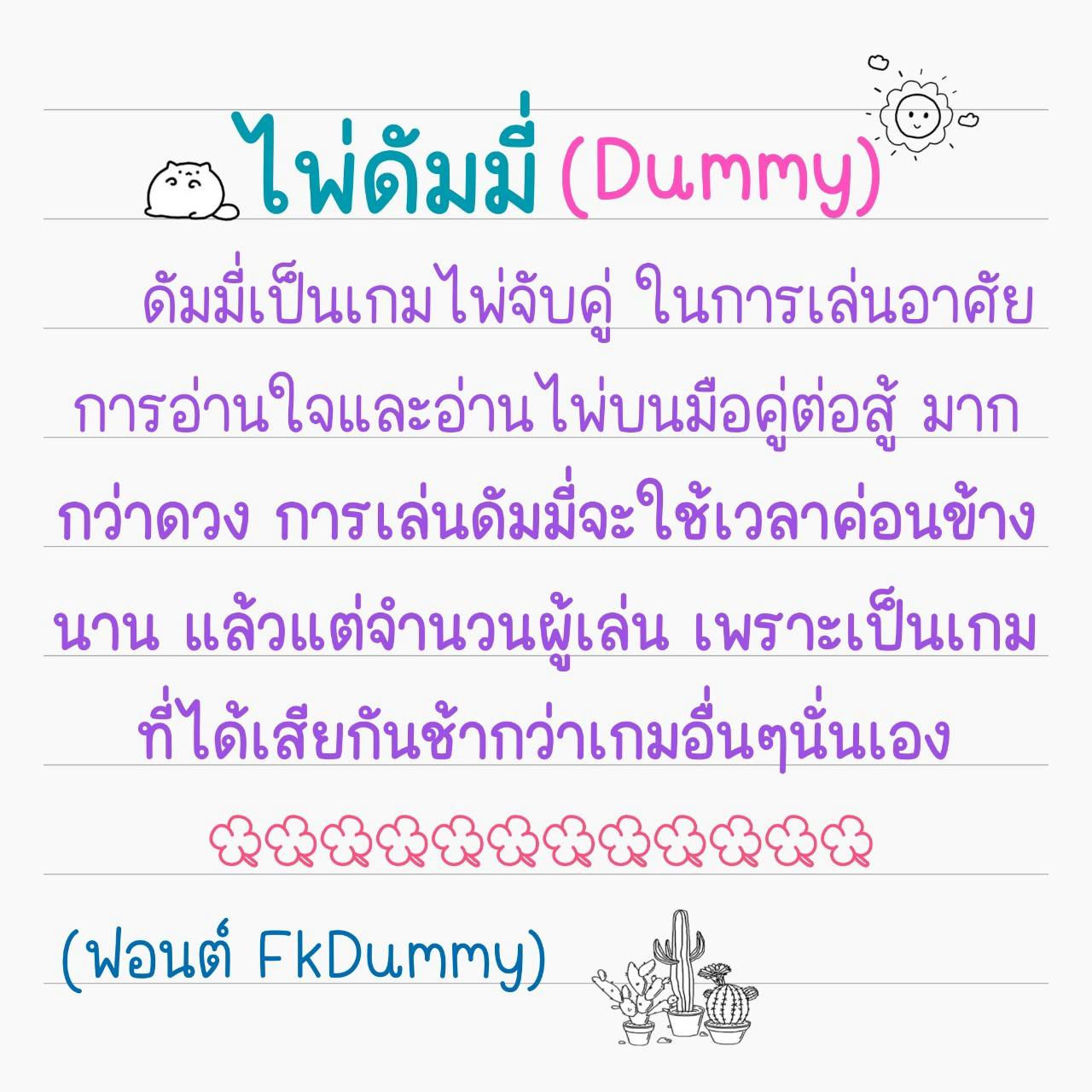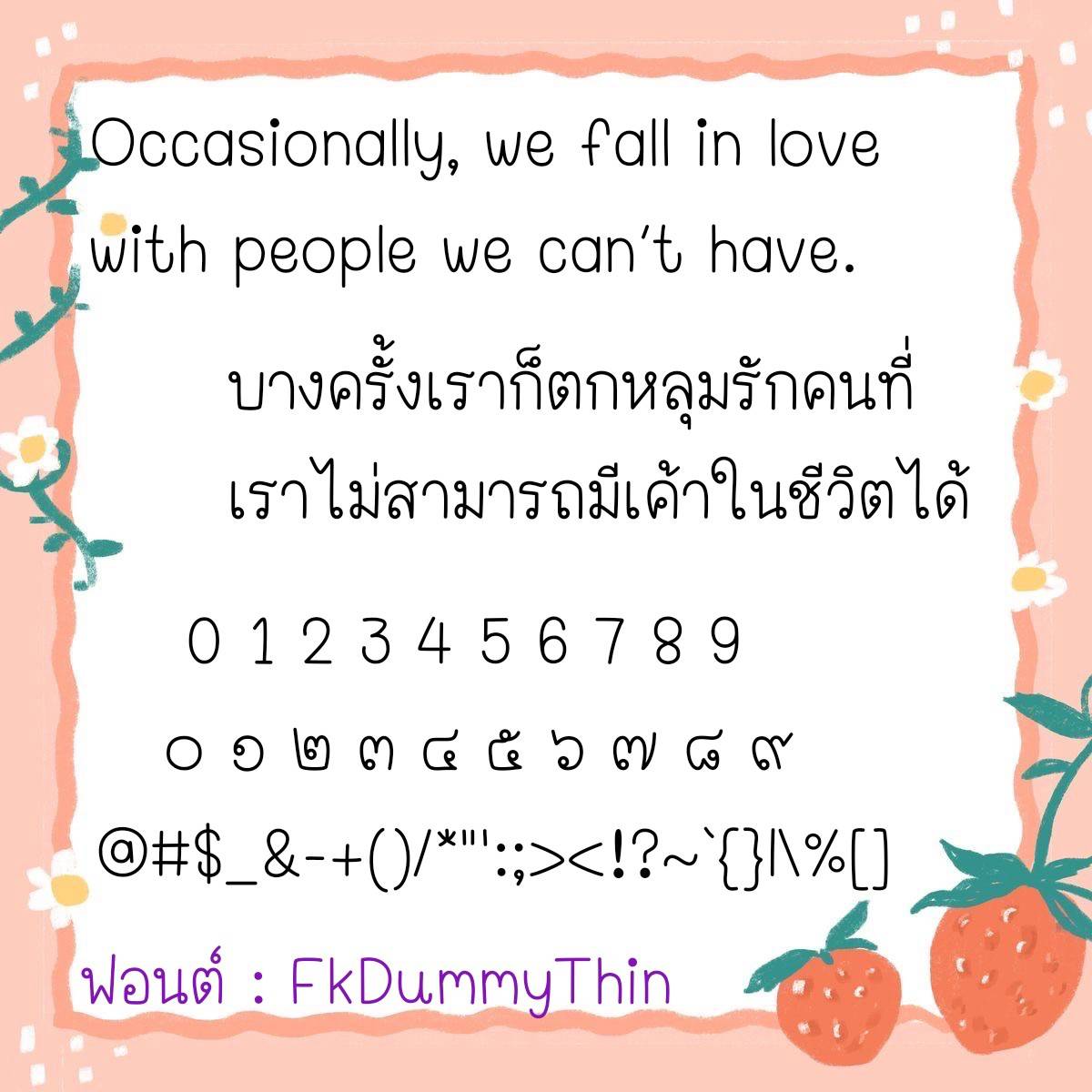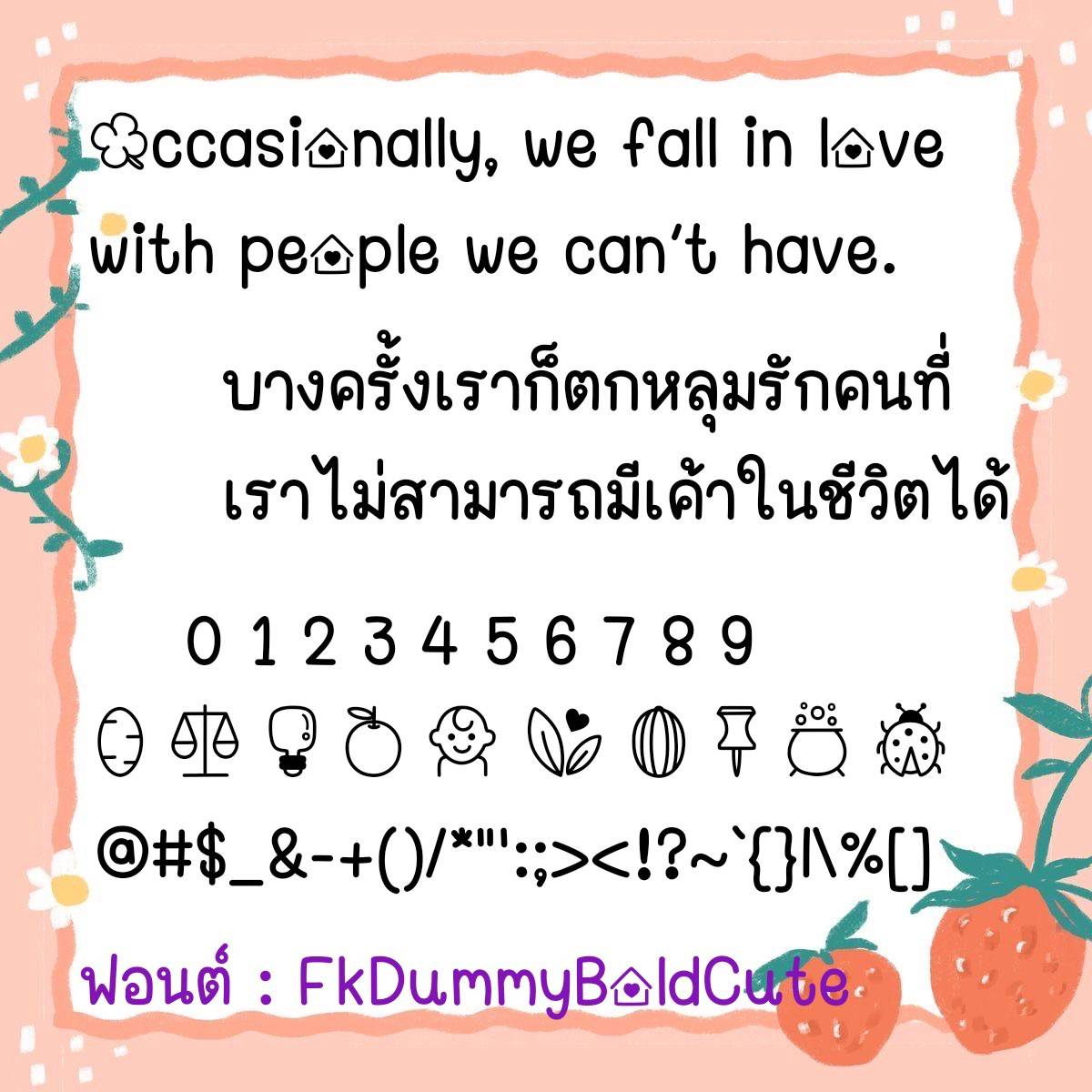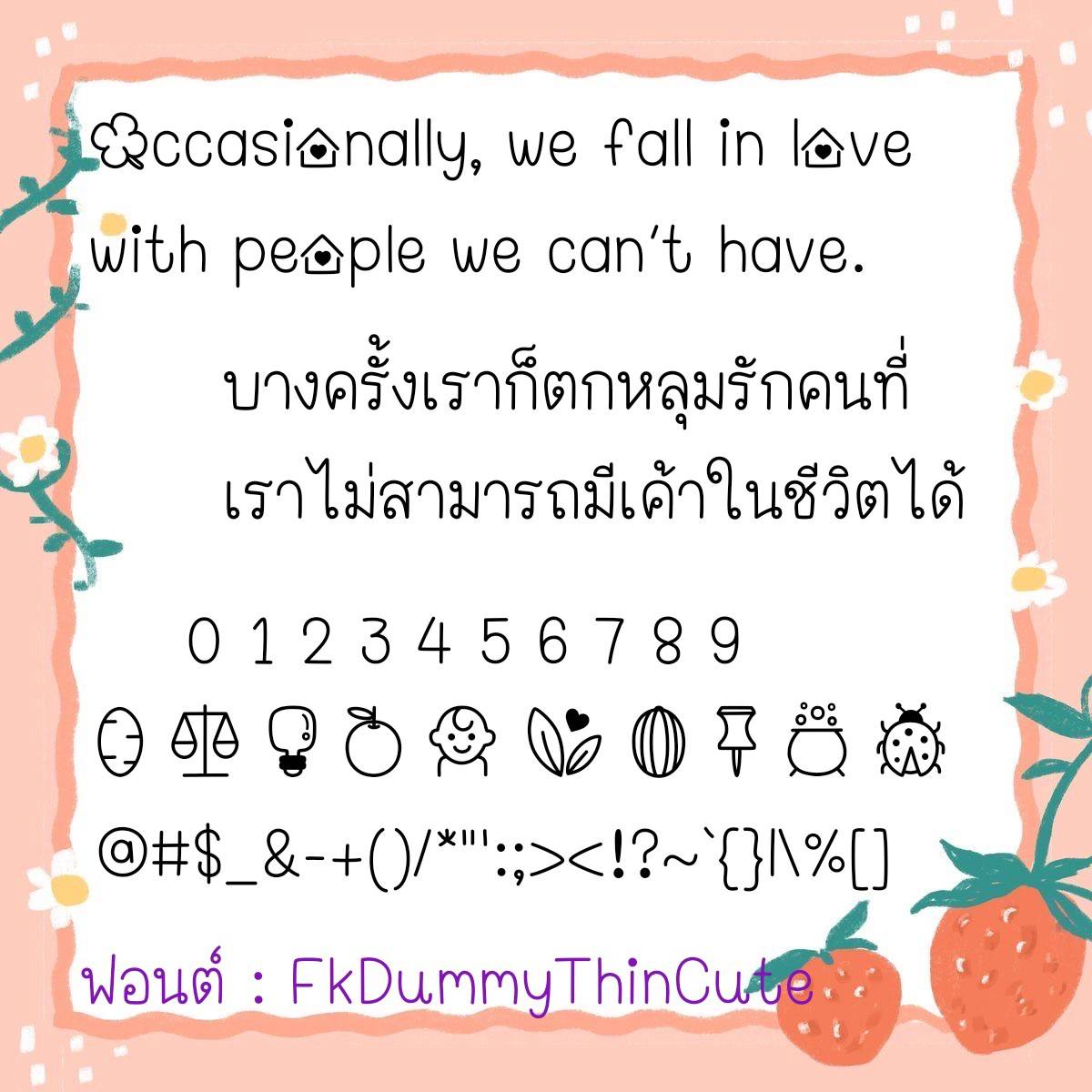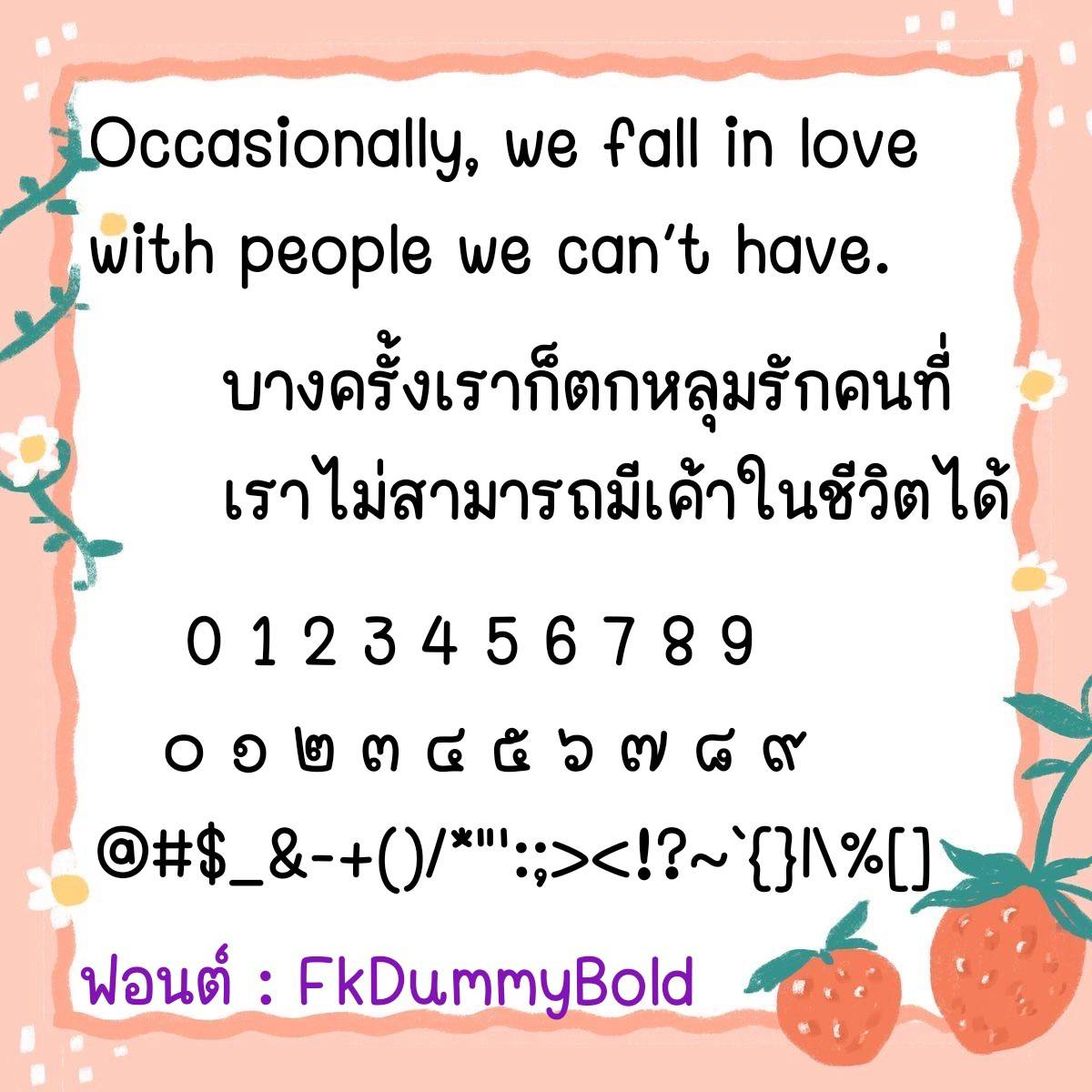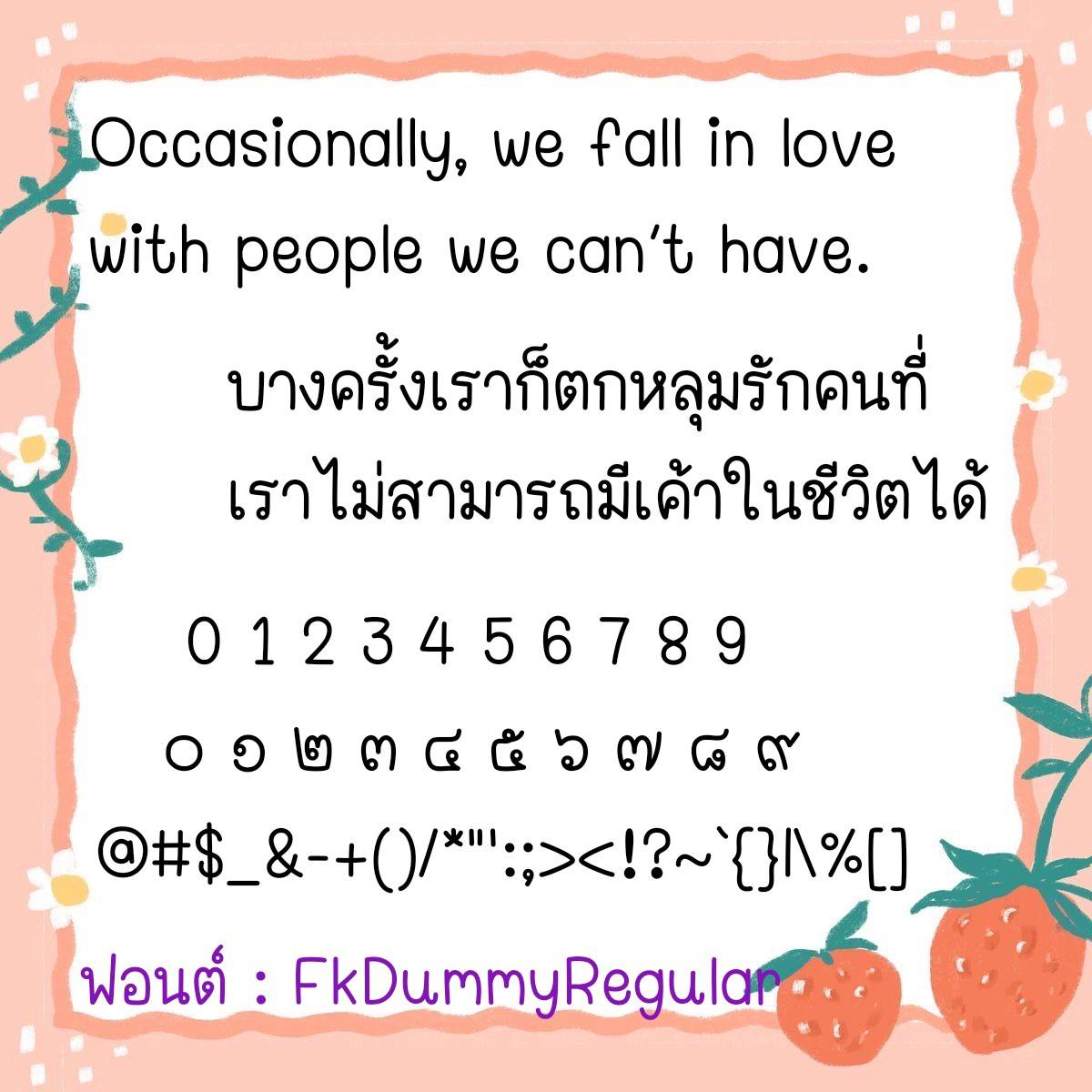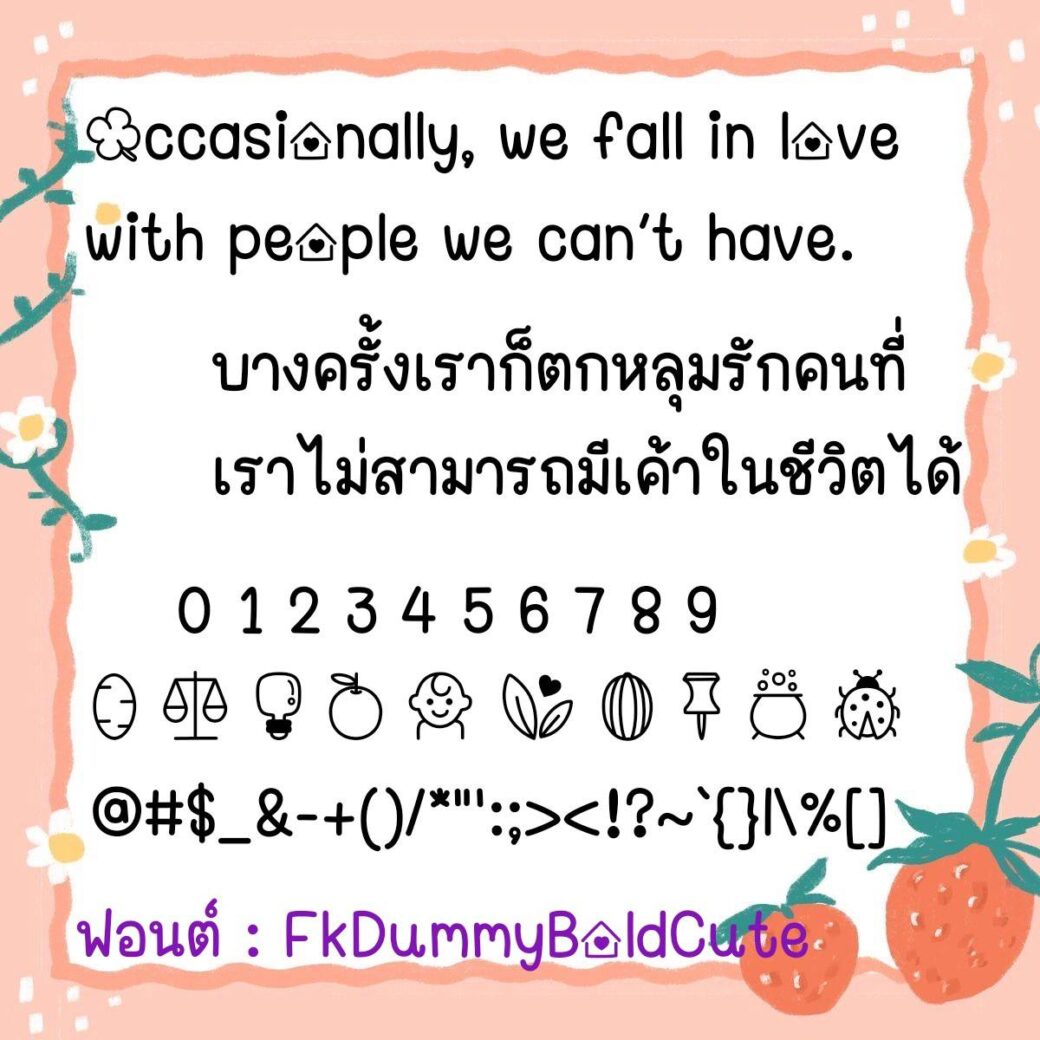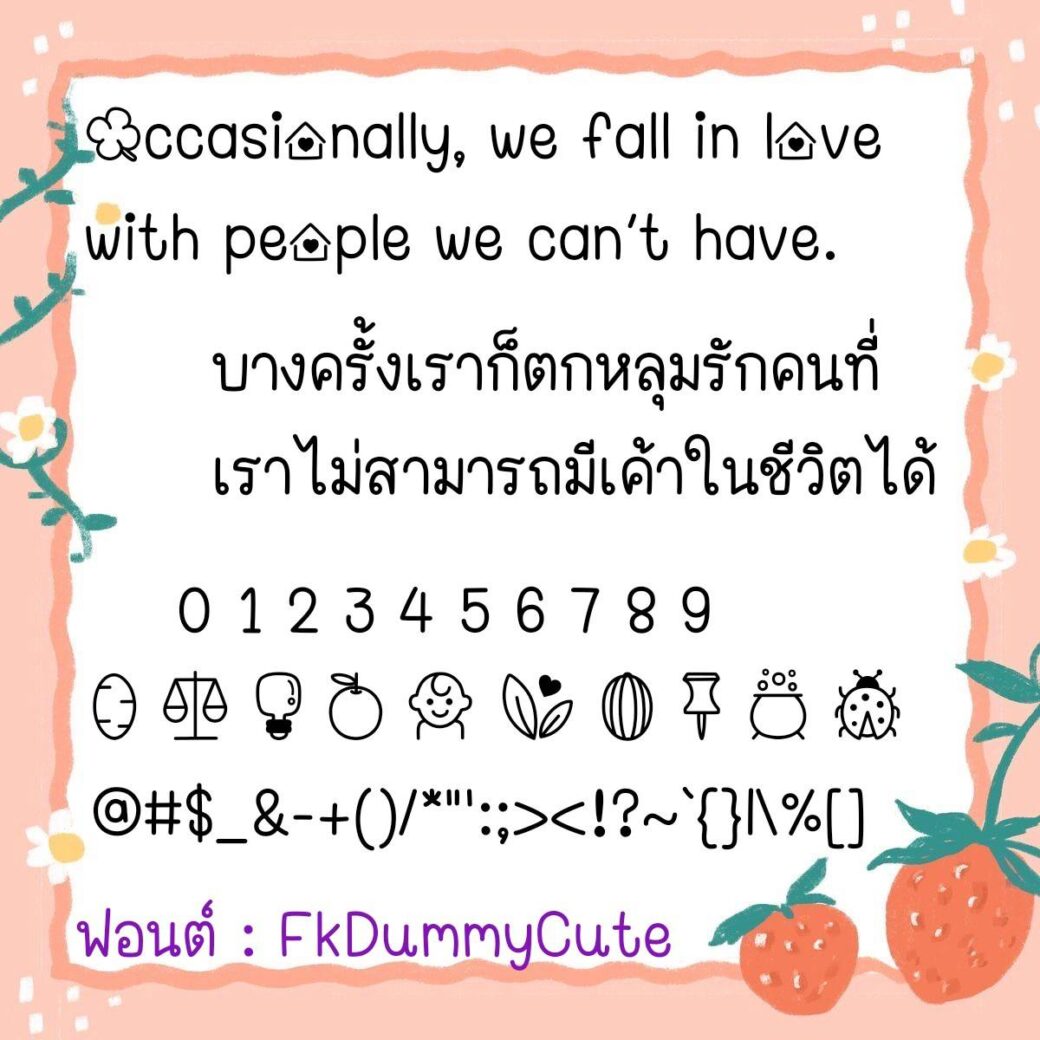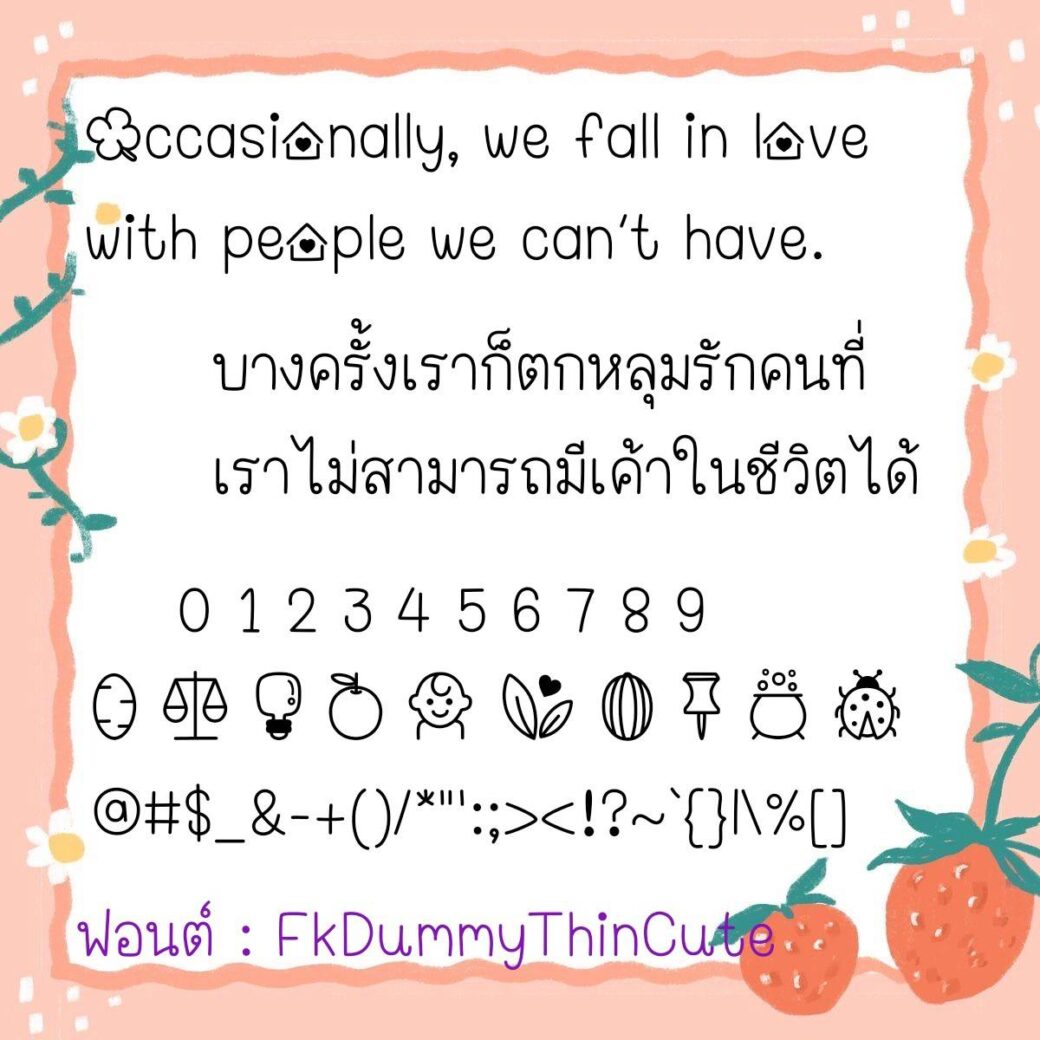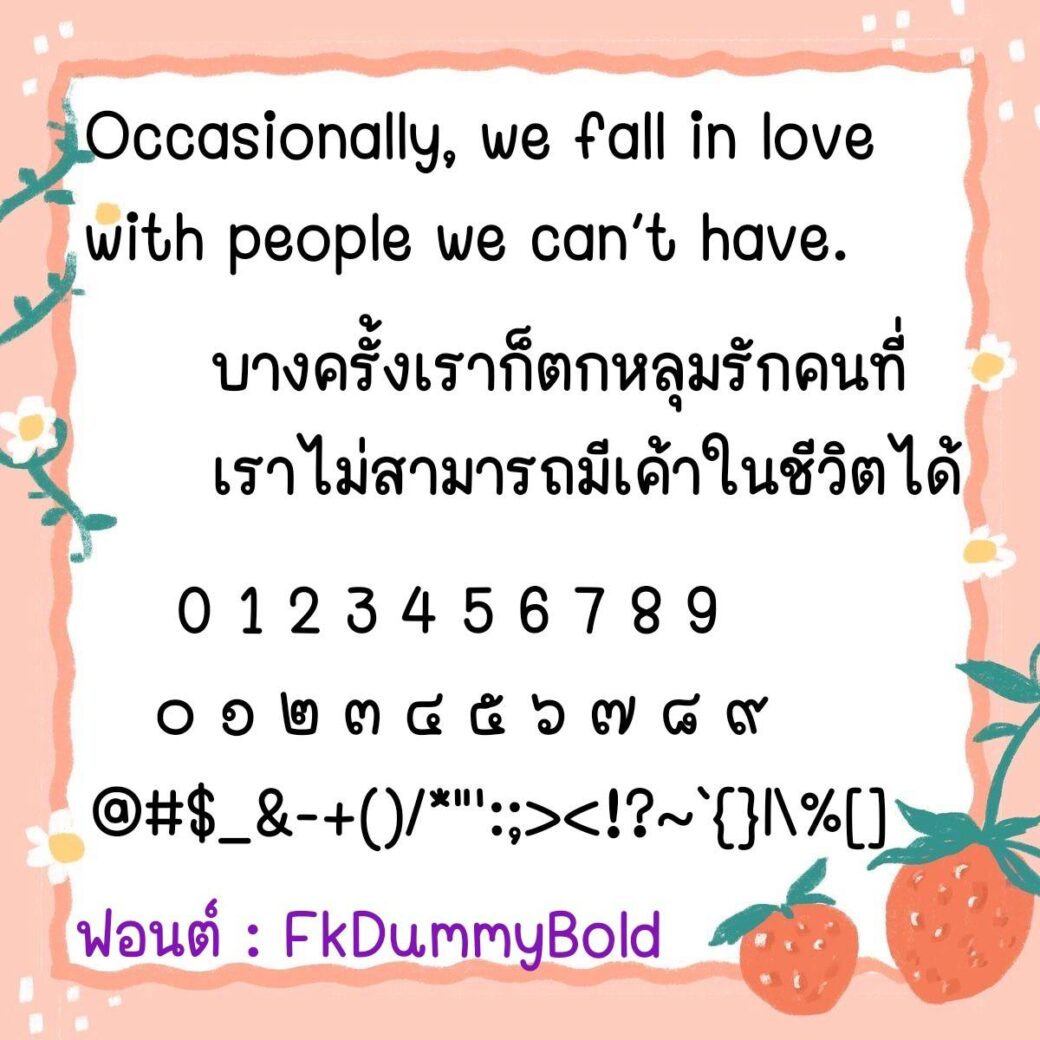
Font FkDummy
ชื่อสินค้า : Font FkDummy 💜
🔸 ฟอนต์ลายมือแนวหัวเล็กขนาดตัวกำลังพอดี ดูมีความเป็นระเบียบเรียบร้อยกึ่งทางการ เน้นอ่านง่ายสบายตา และยังมีไฟล์อิโมจิน่ารักๆ ที่ใช้ปืนเลขไทยให้ด้วยค่ะ 🥰💙
🔹 A handwritten font with small letters and just the right size. It looks neat and semi-formal. It emphasizes easy reading and is pleasing to the eyes. There are also cute emoji files that use Thai numerals. 🥰💙